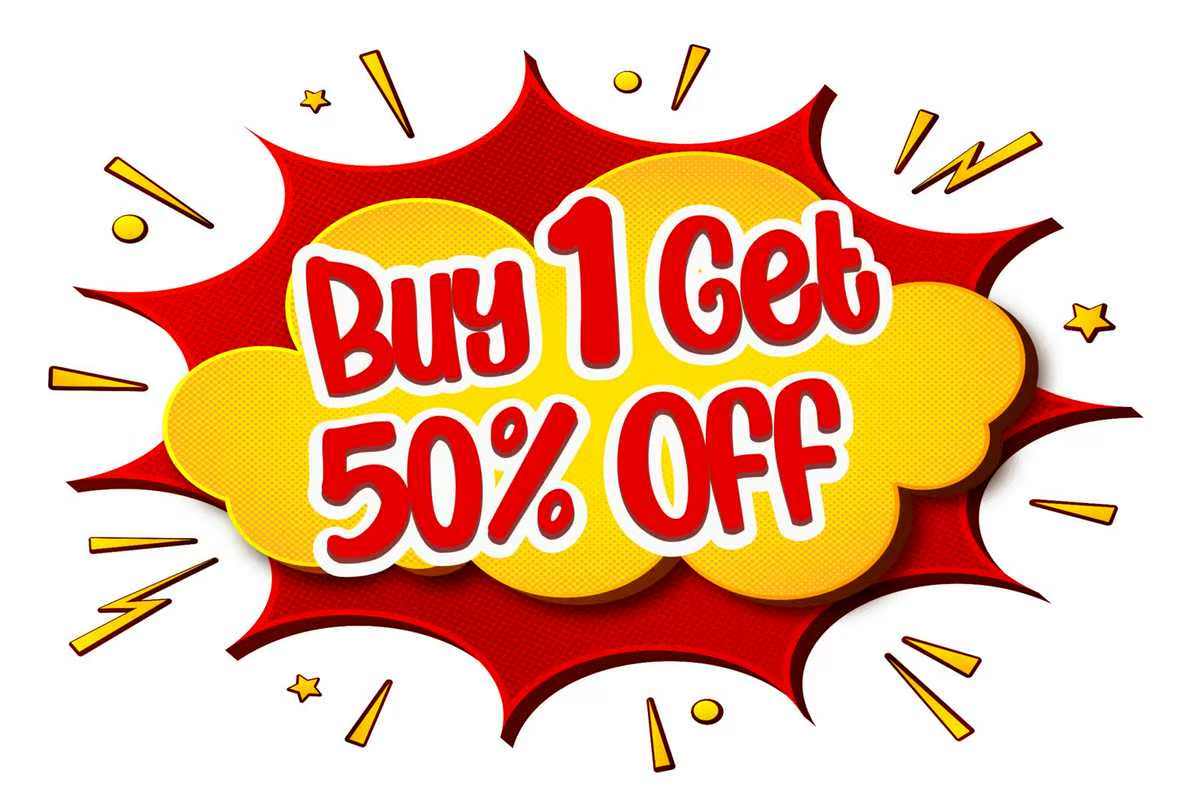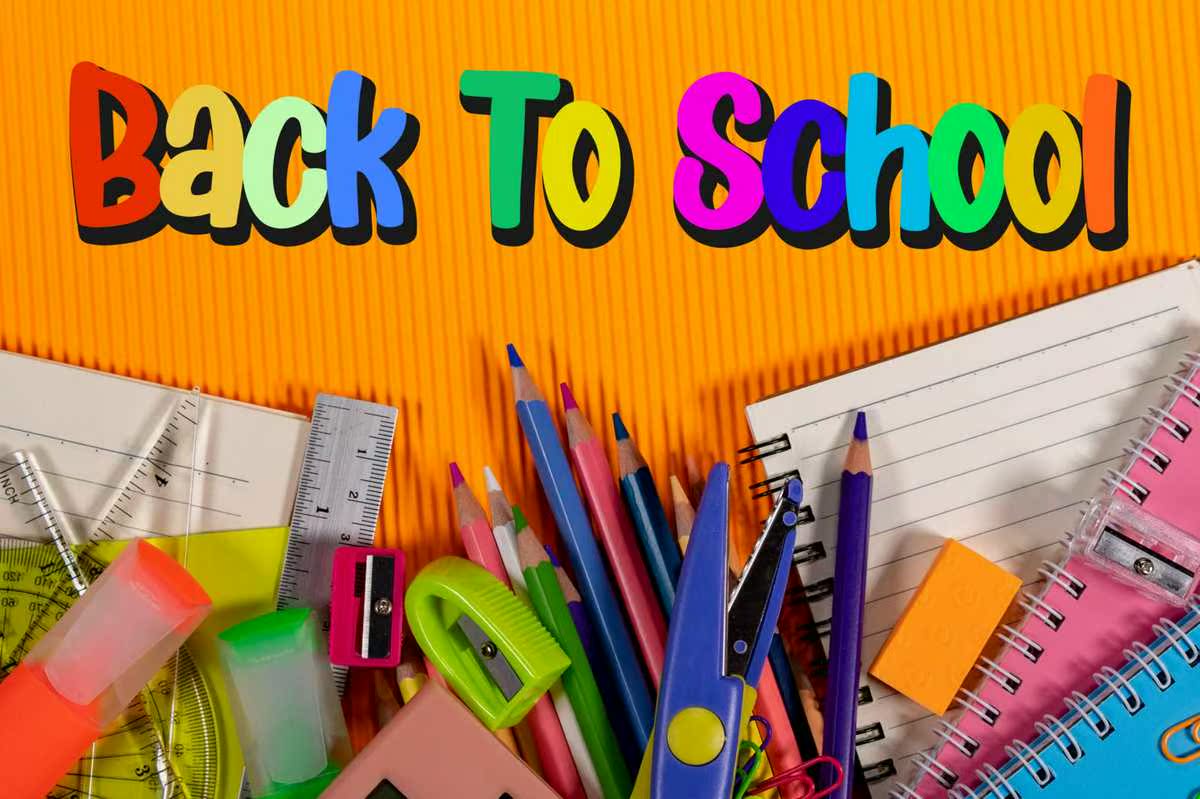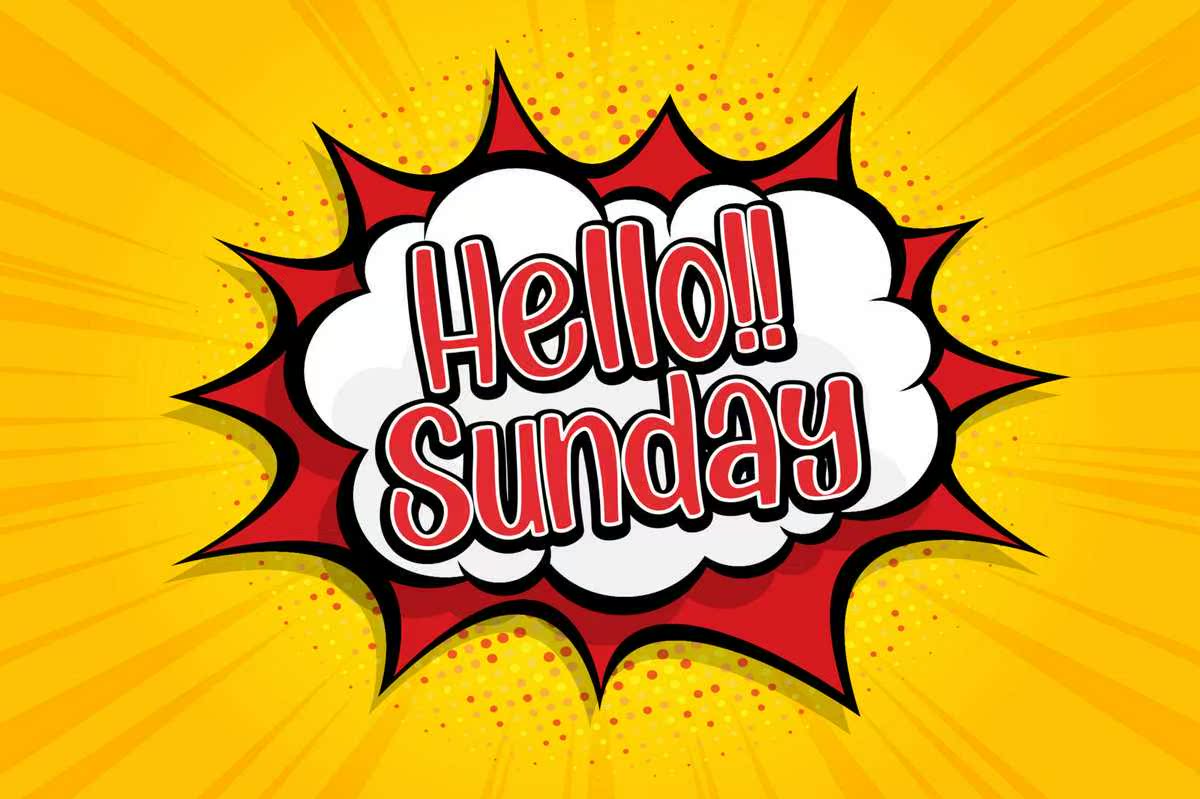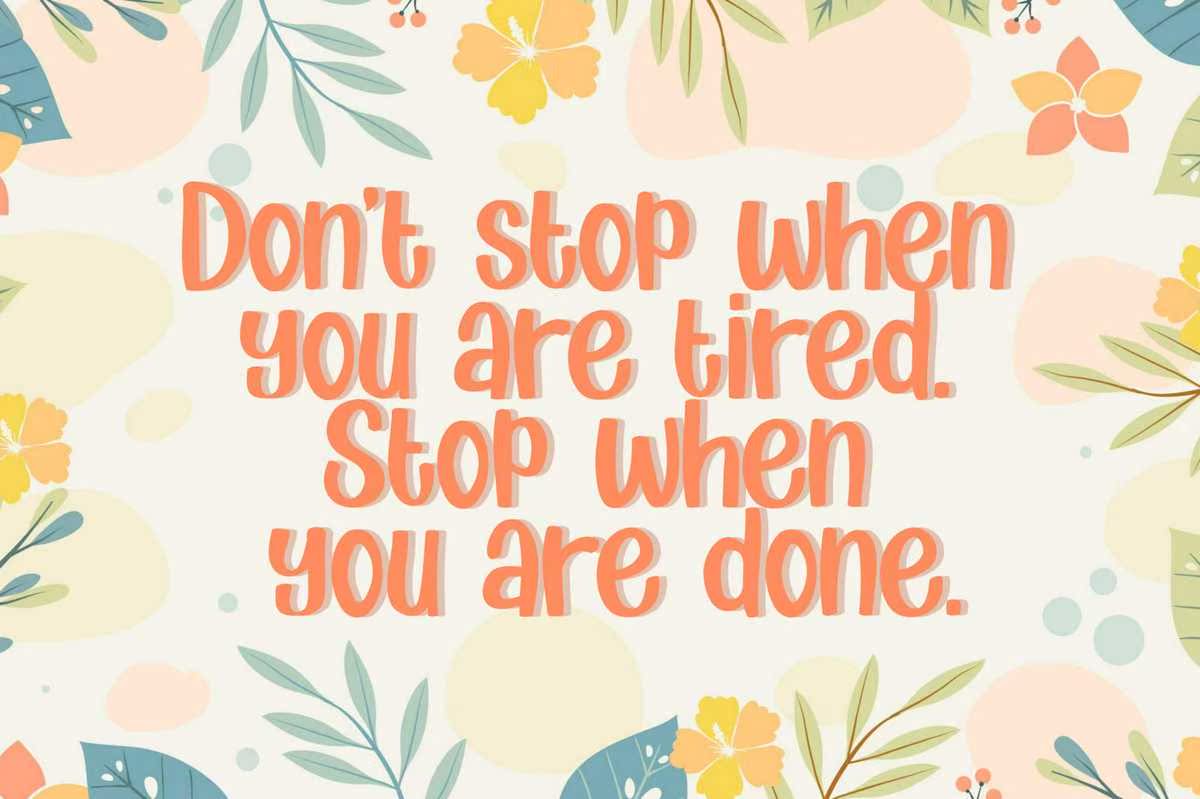
儿童日常使用的字体锐利、可爱、友好。其自然独特的风格使场地特别适合大型游泳池设计。其独特的特点使其适合各种用途,如报价、t恤设计、传单、YouTubechannels、标签、标志以及任何其他需要玩乐触感的设计。这就是你的想象力!儿童日常使用的字体锐利、可爱、友好。其自然独特的风格使场地特别适合大型游泳池设计。其独特的特点使其适合各种用途,如报价、t恤设计、传单、YouTubechannels、标签、标志以及任何其他需要玩乐触感的设计。这就是你的想象力!